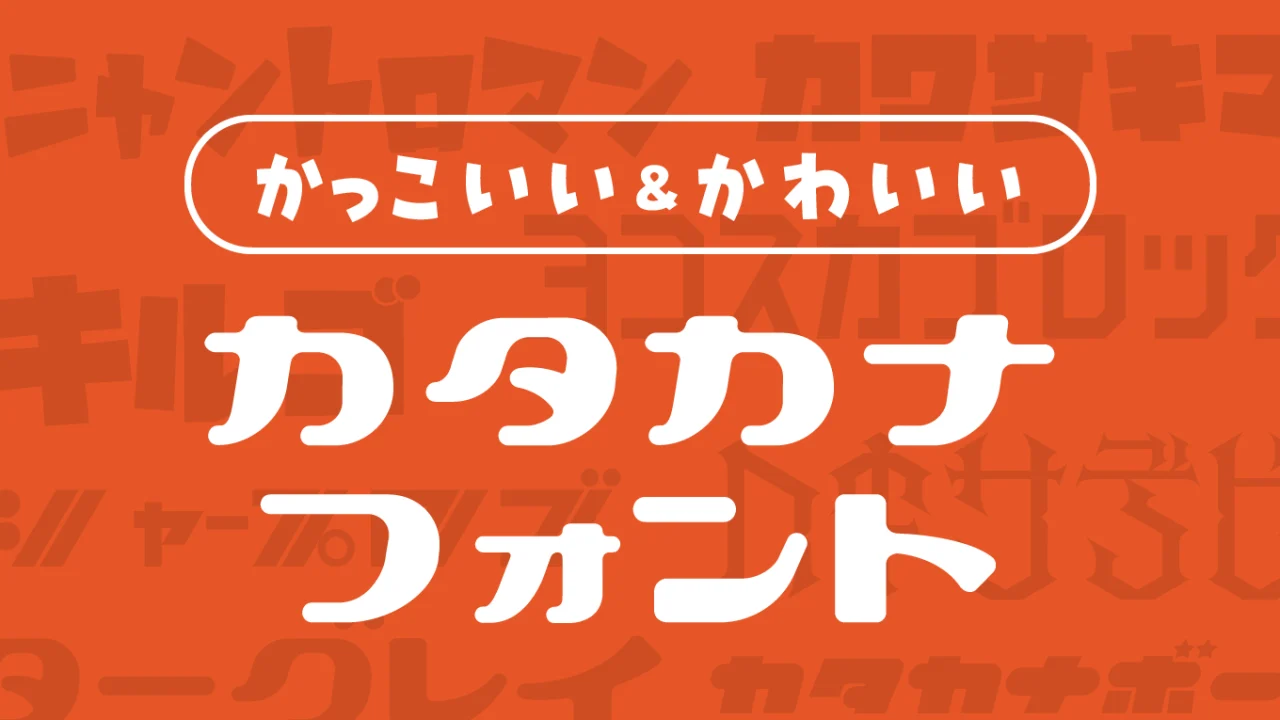
今回は、個性が豊かな「カッコいいカタカナフォント」&「かわいいカタカナフォント」をご紹介します。カタカナフォントは、タイトルロゴや見出しタイトルのさまざまなデザインを作る場面にとっても便利で重宝するフォントです。
カッコいい&かわいいカタカナフォントのまとめ
なお、一部のフォントはカタカナ以外の文字も含まれていますが、カタカナが際立った特徴を持つフォントを選定している点をご理解いただければ幸いです。
以下の画像サンプルは、本記事で紹介しているカタカナのフォントの一部です。このようなカタカナに特徴があるステキなフォントを紹介します。
ビルの谷間と高架下フォントは、漢字とひらがな、カタカナのでこぼこ感が可愛いらしいデザインフォントです。
統一しすぎない字形のデザインがポップでかわいい印象を作り出しているフォントです。漢字も使用できるフォントですが、かな文字がとっても可愛いです。
ナイショ文字
ナイショ文字フォントは、細い横線・太い縦線で構成されるユニークな文字は、一文字一文字メリハリが効いていてインパクトがあり、昭和によく流行っていた字形が懐かしさを感じさせてくれるレトロなフォントになっています。
キッチンカタカナ
キッチンカタカナフォントは、某キッチンメーカー「クリ○ップ」のロゴをベースに製作された極太のカタカナフォントです。
斜めに変形しているのも特徴です、ロゴなどに向いているフォントです。少し斜体がかかったロゴ昔流行りましたね。
ヨコスカブロック
ヨコスカブロックフォントは、空軍の戦闘機に書かれているようなフォントを目指したフォントです。直線的で角張っているフォルムが特徴です。
ミスターグレイ
ミスターグレイフォントはポップな印象とレトロな印象が混じっているようなとっても素敵なカタカナフォントです。
どんなカタカタ文字を打ち込んでもロゴっぽく見えるのが、このフォントのすごいところ。
アトミック
アトミックフォントは、ガチッと太めのシルエットがカッコいいカタカナ・一部記号のみのフォントです。
アンニャントロマン
アンニャントロマンフォントは、ロゴでの利用を想定としたフリーフォントになっています。
インパクトがあるポップで可愛らしいフォントなので、同人誌やゲームなどによく利用されてている人気のフォントです。
ヘキサデビル
ヘキサデビルフォントは、六角形ベースのダークファンタジーを意識した少年の心をくすぐるデザインのフォントです。
呪文のような、魔術書のようなダークな雰囲気がかっこいいカタカナフォントになっています。
キルゴ
キルゴUは、人気マンガ「キルミーベイベー」のタイトルロゴをモチーフに制作されたフォントです。アニメからインスピレーションを受けているため、ゴツゴツしたフォルムがポップな印象を与えます。バナーや動画のアイキャッチ、タイトルやキャッチコピーに使用すると、大きなインパクトを生み出すことができるフォントです。
シャープ旧ロゴ
シャープ旧ロゴフォントは、家電メーカー「シャープ」のかつてのロゴを基に制作されたフォントです。
個々の文字が独特のデザインで構成されており、本文よりもタイトルや店名、会社名などのロゴタイプに適しています。現在のシャープのロゴとは大きく異なり、昭和時代のレトロな雰囲気が漂う魅力的なフォントとなっています。
レトロランプ
まっつん丸の「レトロランプフォント」は、かつての白熱電球「トウランプ®」のロゴレタリングにインスパイアされて制作されたフォントです。
文字の先端に、ちょっとした装飾がこのフォントの印象を作っていますね。どこか懐かしさを感じさせるカタカナフォントです。
きらめきレトロ
きらめきレトロフォントは、文字の先端を装飾されているダイヤや星のようなモチーフが特徴的なフォントです。アンティーク風な文字単体でも使いやすいデザインを想定して制作されています。
ロゴなどそのまま使えそうな可愛らしいフォントです。
カタカナボーイ
カタカナボーイフォントは、「少年が冒険にでる」ような元気いっぱいな印象があるカタカナフォントです。
カタカナで構成されているタイトルやロゴなどは、そのまま使うだけで十分に可愛く仕上がります。テレビ番組やアニメのタイトルロゴなどにも良さそうです。
かりぐらスキップ
ナイショ文字フォントは、細い横線・太い縦線で構成されるユニークな文字は、一文字一文字メリハリが効いていてインパクトがあり、昭和によく流行っていた字形が懐かしさを感じさせてくれるレトロなフォントになっています。
しあさって
しあさってフォントは、文字の書き出しや終わりがさまざまな方向に向いているユニークなフォント、見ているだけで楽しめるようなフォントです。やる気がありそうでなさそうな程良いゆるさと、どことなくレトロ感も特徴です。ひらがな・カタカナのみのフォントです。
レトロゴ
851レトロゴフォントは、電機系会社のロゴに使われていたゴシック書体のようなカタカナフォントです。昭和時代を思い出すレトロな雰囲気があるフォントです。
解星デコール
解星デコールフォントは、文字の先端に装飾されている丸い「うろこ」がユニークなフォントです。文字の先端の「はらい」の部分に丸い装飾が付いているのも特徴です。この装飾がエレガントな優美な印象を表現してくれています。
アンティリム
アンティリムフォントは、象形文字やヒエログリフのような古い遺跡に刻まれてそうな、斜め線を使用せず、直線と曲線だけで構成されたフリーフォント。こどもごころをくすぐられるような遊びごころ満点の可愛らしいフォントです。
カタカナだけではなく、ひらがな・記号・アルファベットも収録されています。
ぎっしりフォント
ぎっしりフォントは、ほぼ正方形内で成形され、文字の形状をぎりぎり保っているぐらい極太で直線的さが特徴的なフォントです。他のフォントでは見たことない表現をしており、とてもステキです。
カタカナだけではなく、ひらがな・記号・アルファベットも収録されています。
鉄路タイプフェイス
鉄路タイプフェイスフォントは、鉄道っぽくてメカっぽいカッコイイフォントです。1文字ごとにいい具合に切り込み(スリット)が入っていることで、ロゴタイトルのように作りこんである文字のようにも見えます。
ベタ打ちしただけでもロゴのように使える素敵でかっこいいカタカナ系フォントです。(一部漢字が収録されているフォントです。)
だるまドロップ
「だるまドロップ(Darumadrop)」とは、「だるま落とし」の意味で、民芸、伝統工芸などの和のキーワードをイメージされた可愛い手描き感のあるフォントです。
文字の輪郭が凸凹しており、墨で書いたようなにじみが和を感じることができるデザインになっています。
なぎの
「なぎの」とは、なぎのフォントは、泡・船・窓など海の要素をモチーフしている手書き風のひらがなと、「ZEN丸ゴシック」を組み合わせた、どこか懐かしさとレトロさを感じる仕上がりになっているフォントです。
あおぼし(Aoboshi One)
「あおぼし(Aoboshi One)」とは、欧文フォント「Copperplate Gothic」をイメージして制作されたフォントになります。
文字の先端に付属されているセリフの飾りが良いアクセントになっており、カッコよさ&かわいいが体現されているフォントです。
ふぁんしーはーと
「ふぁんしーはーと」とは、文字の中にハートのイラストが散りばめられている可愛らしいデザインフォントです。
みんとキッス
「みんとキッス」は、文字の切込みと光沢が入っているレトロ感とラブコメ感の印象があり可愛い仕上がりのデザインフォントです。
ティラノゴチ
「ティラノゴチ」は、元気な小僧をテーマとして制作されたフォントです。元気で明るい様子が文字で表現されているフォントです。
プぷプ
「プぷプ」は、ぷっくらしていて、文字上半になるにつれて線が太くなっていくというユニークなデザインフォントです。かわいいカタカナです。
ネコミミフォント